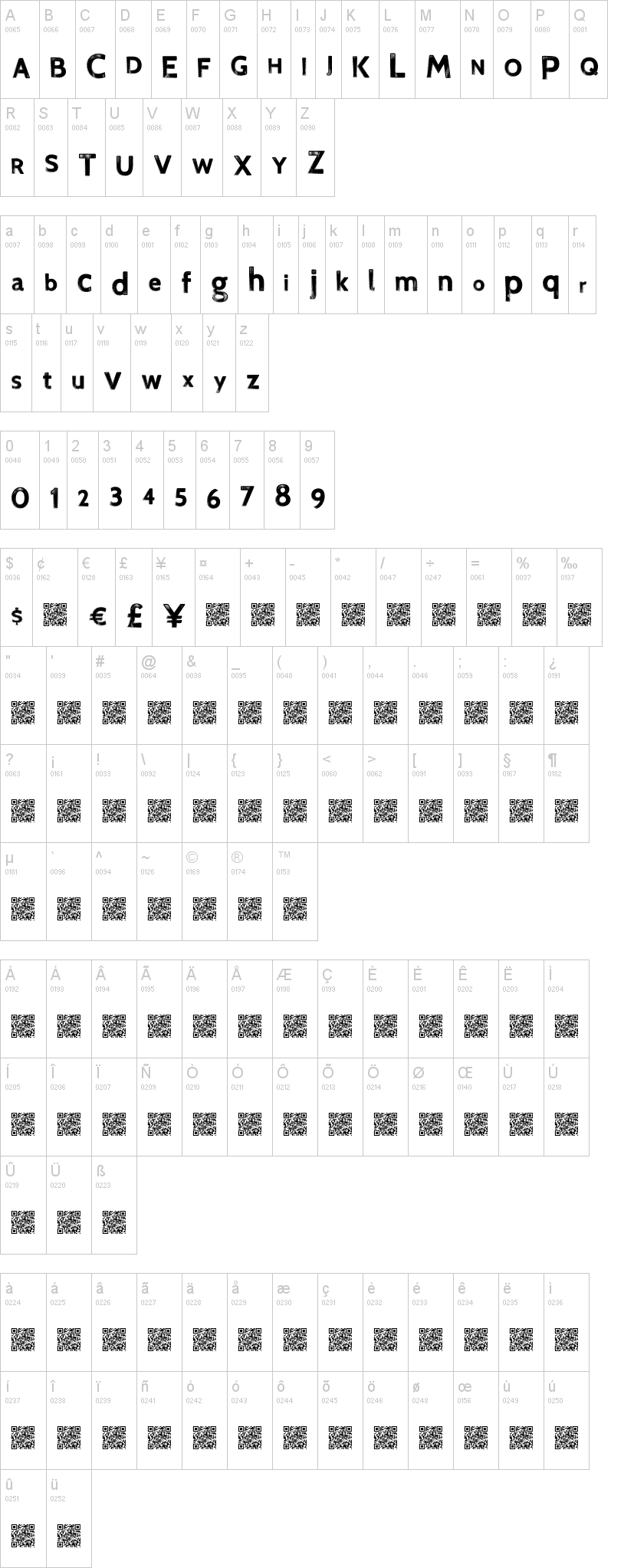
Final Relief
Final Relief 是一款英文字体,由设计师Aaron Amar 所设计,它具有独特的特色,以及细节丰富的外观。它采用粗体、斜体和细体三种字形,具有多种字体特征,可以满足不同的设计需求。其特点是拥有较粗的笔画,圆润的曲线,以及精致的细节,使字体更具有表现力。它适用于商业、宣传、海报等多种设计领域,是一款经典的英文字体。
Final Relief是一款非常不错的手写艺术字体,具有很好的视觉感,适合于文化类的宣传设计、商业类品牌的广告和产品包装设计以及个性化文字排版等较多场景。
Final Relief字符映射图